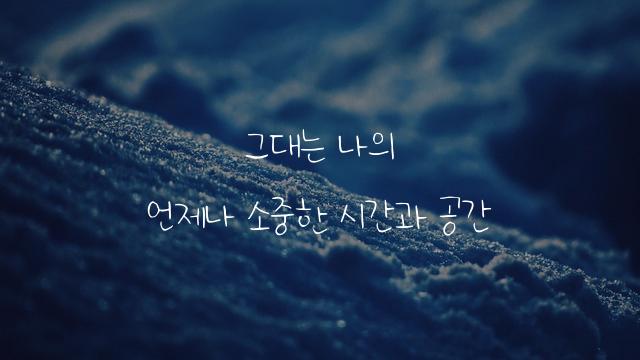
‘안될과학 궤도체’는 온글잎과 안될과학이 협력하여 만든 한글 폰트로, 삐뚤빼뚤하고 펜으로 쓴 듯한 느낌을 표현합니다. 감성적이고 창의적인 디자인이 특징입니다.
안될과학 궤도체은(는)
펜/붓터치 계열의 생김새를 가지고 있으며
웹/앱 디자인, 프레젠테이션, 보고서/문서 등에서 자주 활용되며, 효과적인 메시지 전달에 적합합니다.
이 폰트는 크리에이티브, 기술/IT, 금융/비즈니스 분야에 잘 어울리며,
명확한, 창의적인, 전문적인 느낌을 담고 있는 것이 특징입니다.